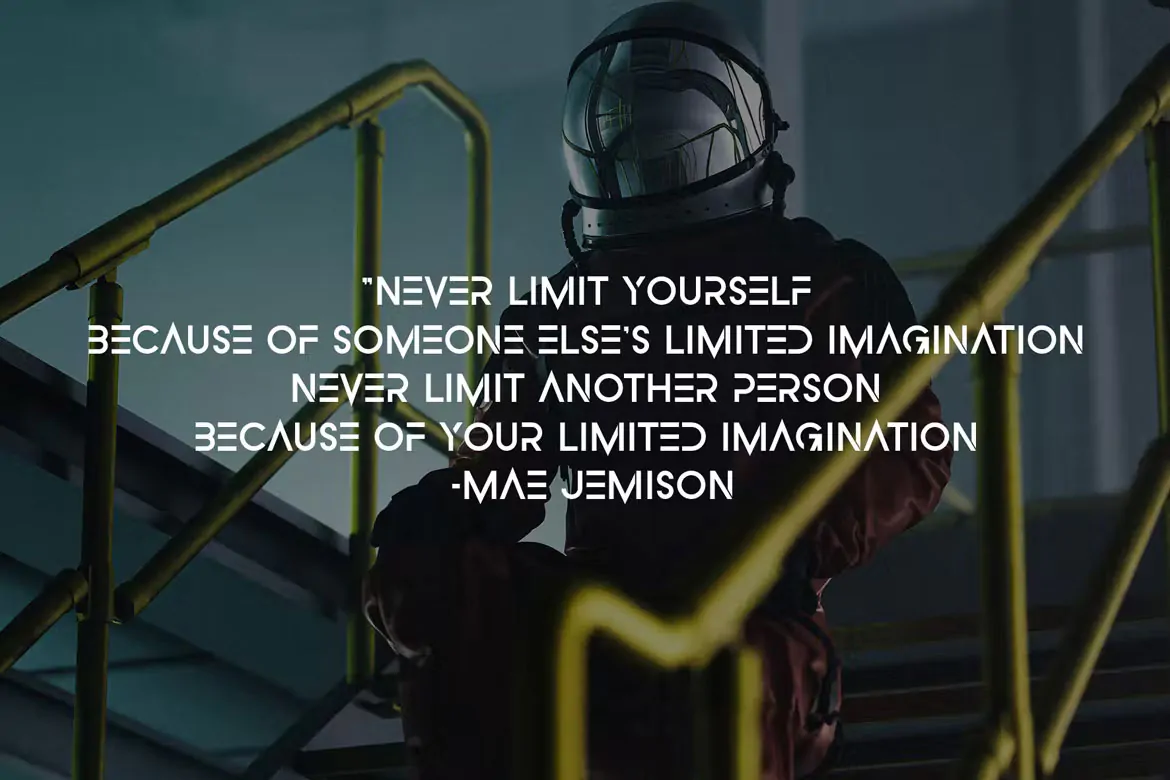
لوگو فونت مدرن انگلیسی Starlynx
لوگو فونت مدرن انگلیسی
لوگو فونت مدرن انگلیسی Starlynx یک قلم فوق العاده زیبا و خلاقانه است که مناسب برای استفاده در طرحهای گرافیکی مختلف همچون طراحی لوگو، پوستر، کارت ویزیت، بروشور، تراکت، بسته بندی محصولات و … میباشد.